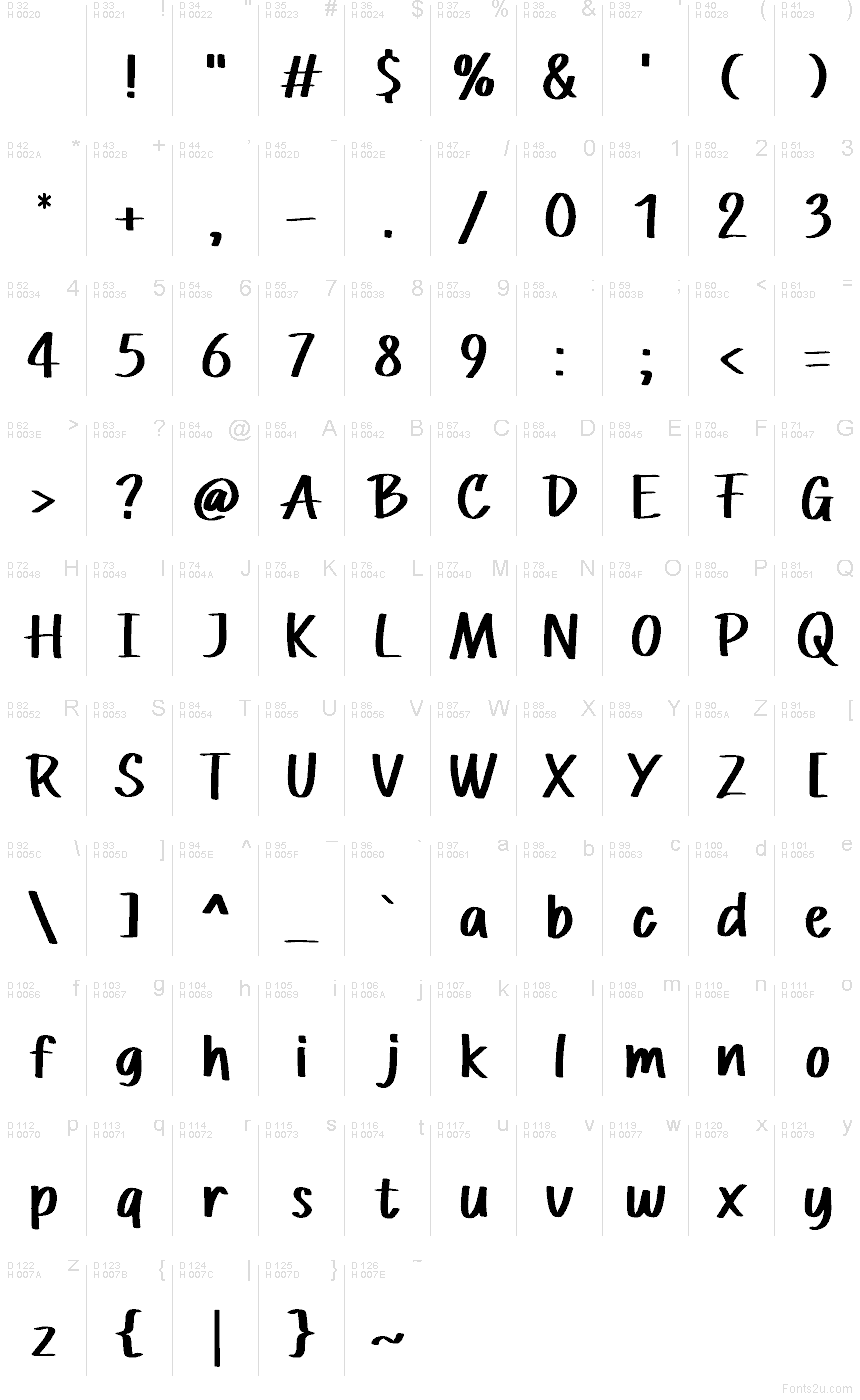
Asphalt Effect від Hello Good Studio - це безкоштовний рукописний шрифт із легкими мазками пензля та округлими формами, що надають літерам неформального й дещо грубуватого вигляду. Нерівні краї та плавні з'єднання створюють динамічний «живий» ритм письма, не виглядаючи при цьому неохайно.
Asphalt Effect чудово підходить для цитат на плакатах, брендингу кафе, графіки для соціальних мереж, етикеток на пакуваннях і неформальних логотипів, оскільки скетчева текстура штриха додає дизайну індивідуальності й відчуття «ручної роботи». Цей безкоштовний шрифт також ідеально підходить для коротких запрошень і підписів, де ви хочете отримати невимушений рукописний ефект замість суворого друкованого стилю.